Thành lập vào năm 1994, Amazon giờ đã phát triển thành một hệ sinh thái với nhiều hạng mục khác nhau như Prime Video, Alexa, Amazon Basics, Amazon Photo,... Tuy nhiên, những ứng dụng này như một công ty độc lập và thiếu sự liên kết với nhau. Chính vì thế, Amazon vừa trải qua một cuộc “lột xác” về hình ảnh với quy mô lớn, kết hợp hơn 50 thương hiệu con thành một hệ sinh thái thương hiệu thống nhất.
James Greenfield - Nhà sáng lập của agency Koto đồng thời là agency thiết kế đứng sau dự án làm mới Amazon, chia sẻ rằng việc tái cấu trúc toàn bộ danh mục thương hiệu của Amazon là “một trường hợp hiếm gặp” bởi: “Amazon đôi khi giống như hàng chục công ty khác nhau trong cùng một tổ chức. Chúng tôi phải sẵn sàng đương đầu với thử thách đó”.
Bộ nhận diện thương hiệu cũ của hơn 50 thương hiệu thuộc Amazon
Sự đa dạng và quy mô lớn của hơn 50 thương hiệu con trực thuộc Amazon đã trở thành một bài toán phức tạp cho agency đảm nhận việc tái cấu trúc thương hiệu. Trước kia, việc triển khai nhận diện thương hiệu của Amazon khá rối rắm và thiếu đồng bộ. Nhiều tài sản thương hiệu như logo, màu sắc, font chữ, không được sử dụng đúng cách. Do đó, nhóm thiết kế của Koto phải điều chỉnh mọi quyết định thiết kế sao cho phù hợp với tổng thể của Amazon.
Những logo cũ của Amazon từ khi đi vào hoạt động cho đến trước khi tái thiết kế
Logo biểu tượng của Amazon từ lâu đã được nhiều người yêu thích nhờ thiết kế thông minh, thể hiện dải sản phẩm từ A đến Z và "nụ cười" quen thuộc. Ở phiên bản mới, nụ cười này được làm sâu hơn, rõ nét hơn và phần mũi tên cong cũng được nhấn mạnh thêm để tăng tính nhận diện.
Logo mới của thương hiệu có thiết kế gọn hơn, phần chân chữ A thon hơn và nụ cười sâu hơn
Toàn bộ hệ thống hình ảnh thương hiệu cũng được tinh giản để tạo sự thống nhất thị giác. Mỗi logo con đều được điều chỉnh để đảm bảo sự đồng bộ, đồng thời Amazon cũng phát triển font chữ riêng là “Amazon Logo Sans” giúp tạo nên diện mạo nhất quán và có thể sử dụng cho tất cả thương hiệu con. Ngoài ra, các thương hiệu con cũng được chia thành từng “cohort”, tức là các nhóm thương hiệu có cùng định hướng, giúp tổ chức hệ thống thương hiệu đa dạng của Amazon một cách logic và dễ điều hướng.
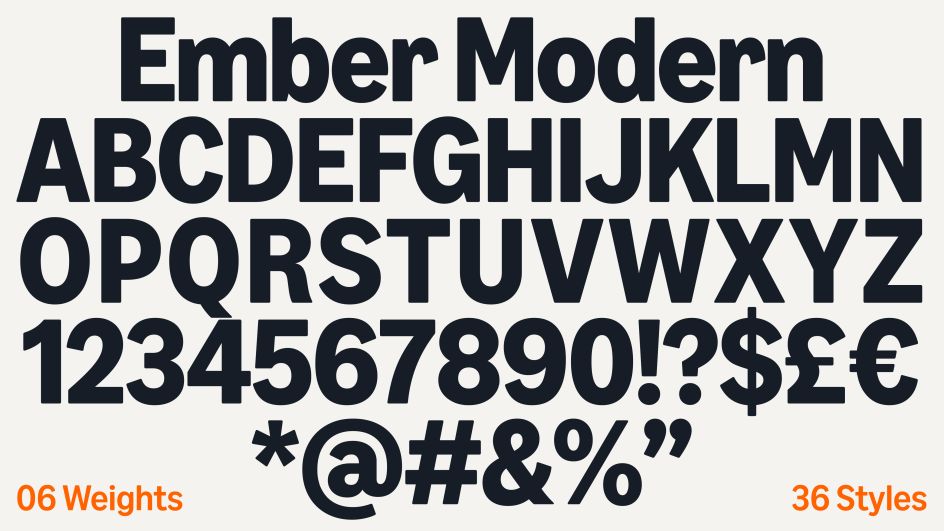
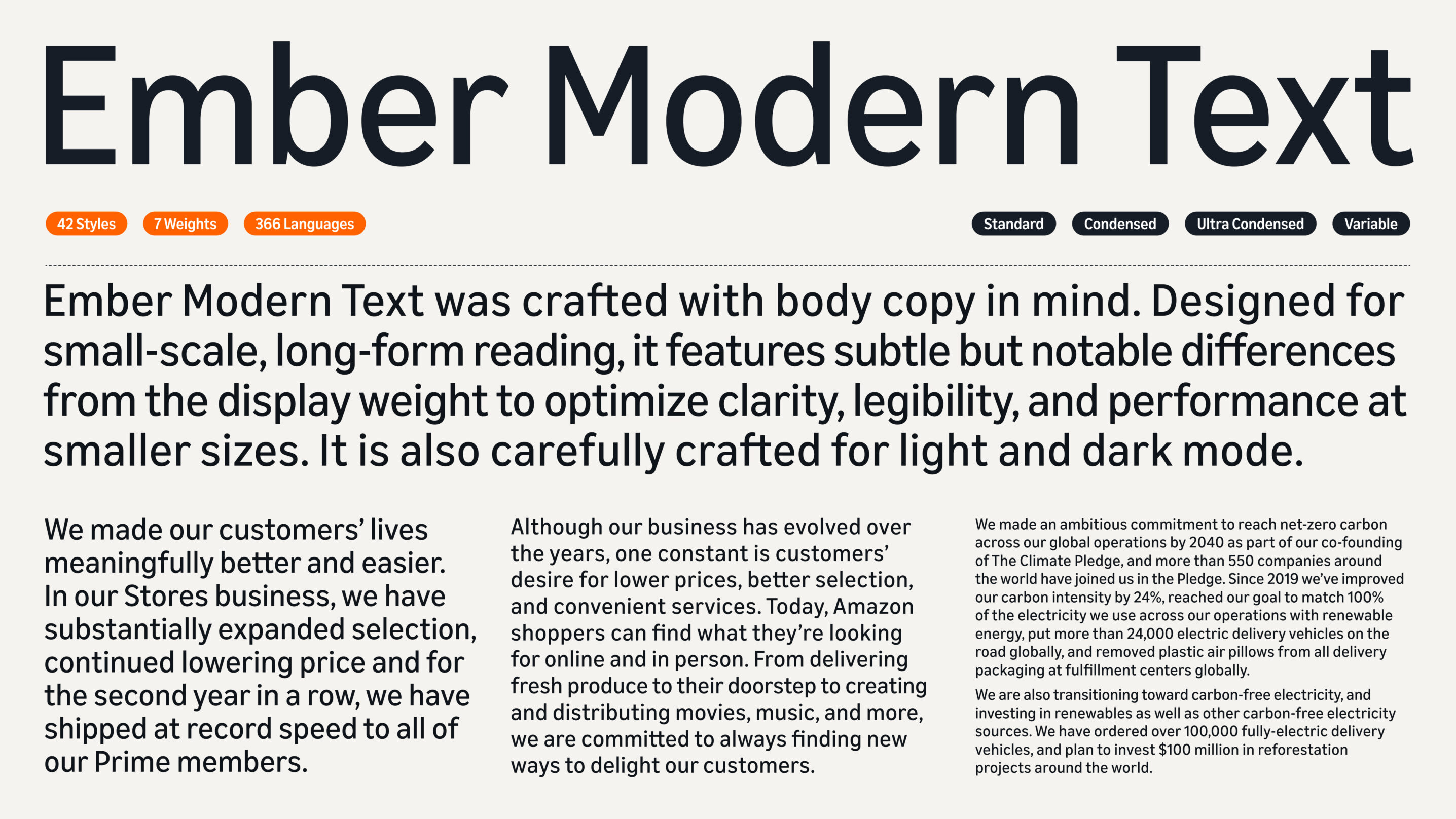
Amazon đồng thời ra mắt bộ font mới nhằm đồng bộ toàn bộ thiết kế các thương hiệu trên toàn cầu
Về kiểu chữ, Amazon đã nâng cấp từ font Ember cũ (vốn được thiết kế riêng cho Kindle) sang một phiên bản mới có tên Ember Modern. Ember cũ từng bị giới hạn về khả năng ứng dụng, khiến các thương hiệu con phải sử dụng nhiều font thay thế thiếu đồng nhất. Ember Modern được Koto phát triển để có thể đáp ứng cả nhu cầu hiển thị ấn tượng trong các chiến dịch quảng bá lẫn giao diện sử dụng hằng ngày, đồng thời hỗ trợ tới 364 ngôn ngữ – giúp Amazon giữ được bản sắc trên toàn cầu.
Màu sắc thương hiệu cũng được tinh chỉnh, xoay quanh hai tông chủ đạo: Smile Orange – cam biểu tượng của Amazon và Prime Blue – xanh kỹ thuật số nổi bật của dịch vụ Prime. Bên cạnh đó, hệ thống icon cũng được thiết kế lại toàn diện để tạo cảm giác thống nhất, dễ nhận diện và phù hợp cho mọi quy mô hiển thị.
Màu sắc trước và sau khi thay đổi của Amazon và Prime
Bộ nhận diện mới đã bắt đầu xuất hiện trên nhiều kênh như màn hình kỹ thuật số, xe giao hàng, đồng phục nhân viên và bao bì sản phẩm. Tuy nhiên, mục tiêu của lần tái thiết này là sự chuyển mình nhẹ nhàng nhưng cần thiết nên nhiều người dùng có thể vẫn chưa nhận ra sự thay đổi của thương hiệu.
Amazon đang bước sang một kỷ nguyên mới về sự chuyên nghiệp và hiện đại mà không cần xóa bỏ những giá trị cốt lõi đã tạo dựng từ trước. Đây chính là một ví dụ điển hình về cách một thương hiệu có thể thay đổi và phát triển mà không đánh mất bản sắc vốn có của thương hiệu.
Những thiết kế sau khi thay đổi có phần nhất quán và đồng bộ hơn
Với diện mạo mới được triển khai trên 15 thị trường toàn cầu, lần tái thiết thương hiệu này mang phong cách tối giản, chỉn chu, cho thấy việc quay trở lại những yếu tố cơ bản có thể mang đến sự nhất quán và uy tín mà vẫn giữ lại nụ cười đặc trưng của Amazon.